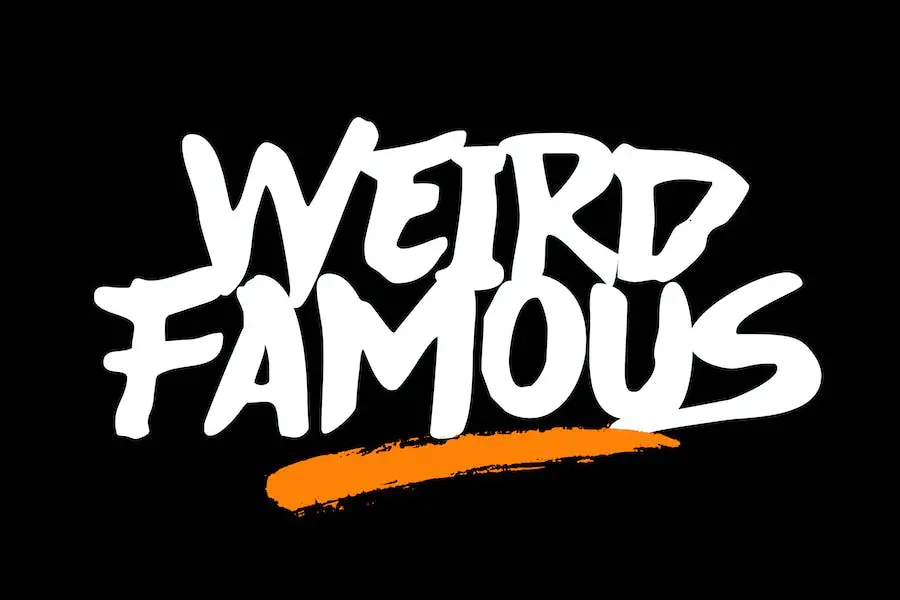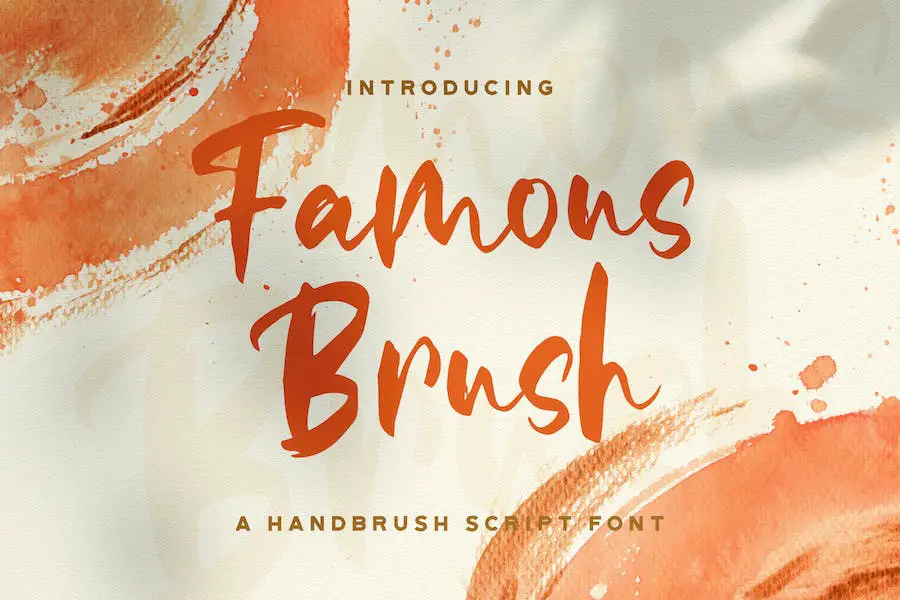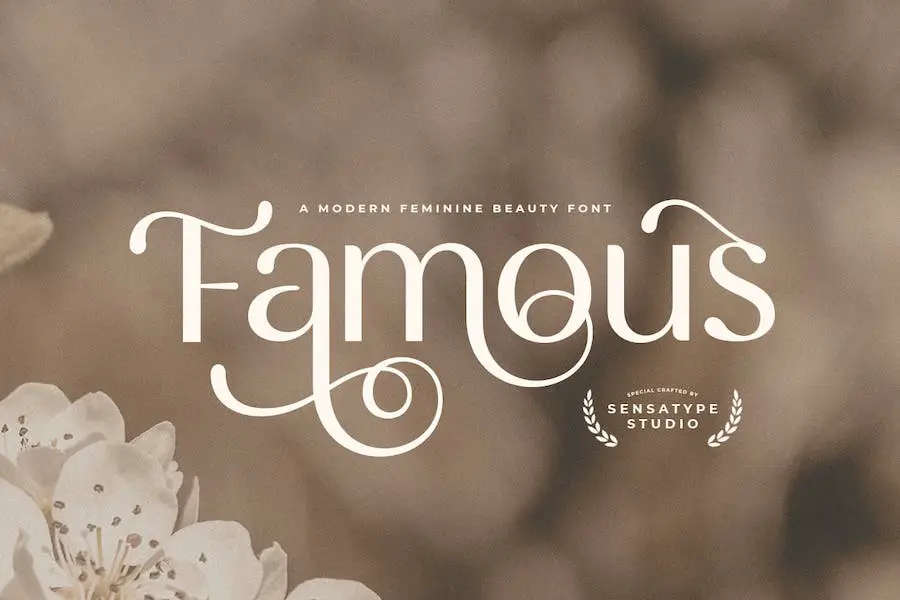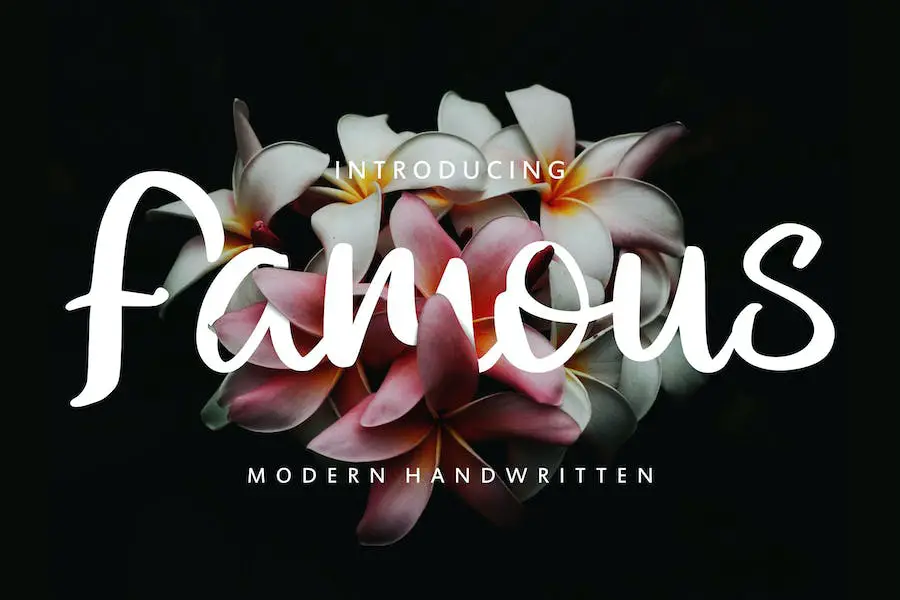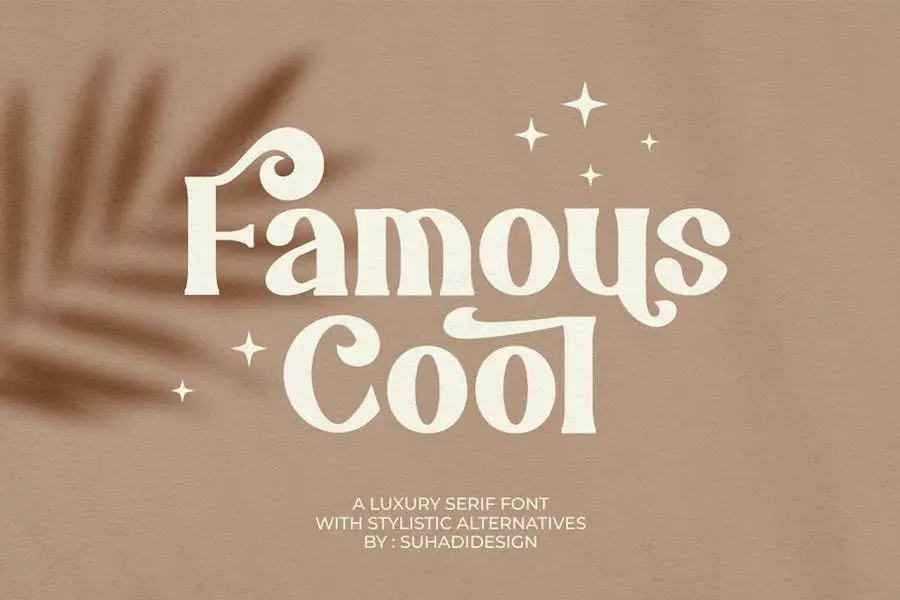
Las 26 fuentes más famosas de 2023 (gratis y premium)
Publicado: 2023-09-22¿Eres un diseñador gráfico en busca de la fuente perfecta para realzar tus proyectos? ¡No busque más! En esta publicación de blog, exploraremos las fuentes más famosas que seguramente mejorarán su trabajo de diseño.
Quizás se pregunte: "¿Qué hace que una fuente sea famosa?" o "¿Cómo pueden estas fuentes mejorar el diseño de mi proyecto?" Bueno, quédate porque tenemos todas las respuestas para ti.
En este artículo, nos sumergiremos en el mundo de la tipografía y mostraremos algunas de las fuentes más icónicas y conocidas que han tenido un impacto significativo en la industria del diseño.
Desde fuentes serif clásicas hasta fuentes de visualización modernas y extravagantes, cubriremos una amplia gama de estilos y su uso. Así que prepárate para inspirarte y descubrir nuevas fuentes que llevarán tus proyectos de diseño al siguiente nivel.
Comencemos nuestro viaje de exploración de fuentes examinando las características de estas fuentes famosas y comprendiendo su popularidad entre los diseñadores. Discutiremos el significado histórico, las asociaciones culturales y el impacto que estas fuentes han tenido en las tendencias de diseño populares.
Con cada fuente, le proporcionaremos datos y estadísticas interesantes, lo que le brindará una comprensión más profunda de su uso y popularidad.
Entonces, ya sea que esté diseñando un logotipo, creando un póster o simplemente necesite una fuente nueva para mejorar su contenido digital, este artículo es su guía para las fuentes más famosas disponibles.
Las mejores fuentes famosas premium
¿Buscas mejorar tus proyectos de diseño? No busques más que nuestra colección seleccionada de las mejores fuentes famosas premium. Estas fuentes seguramente agregarán un toque de sofisticación y creatividad a tu trabajo. ¡Echa un vistazo a los siguientes productos y prepárate para inspirarte!
Famoso
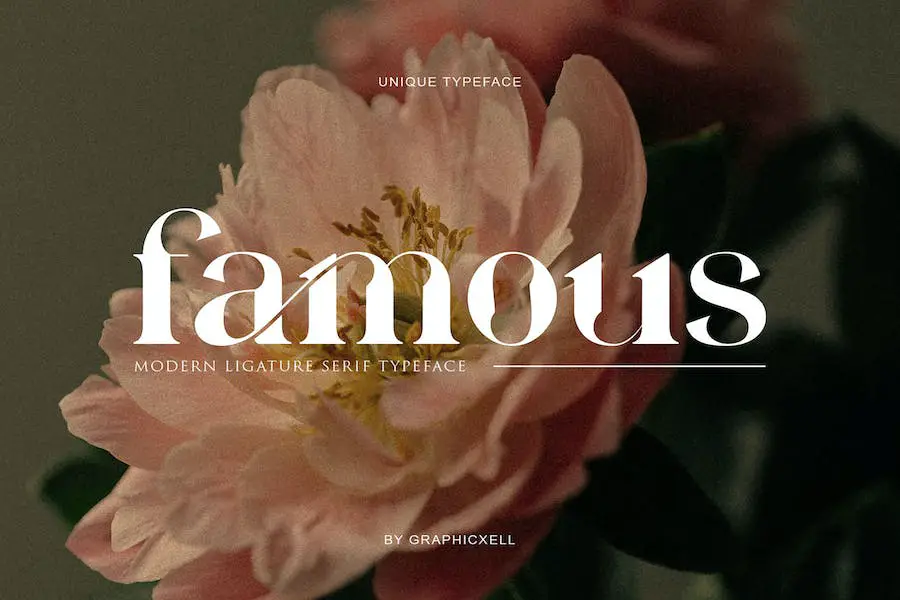
Famous es una fuente Serif que se inspira en famosos logotipos minimalistas. Esta fuente es ideal para diseñadores gráficos que buscan mejorar el diseño de sus proyectos, ya sea creando plantillas, folletos, videos o marcas para publicidad.
Con su estilo elegante y minimalista, Famous añade un toque de profesionalismo y sofisticación a cualquier diseño. Sus líneas limpias y curvas elegantes lo hacen adecuado para una amplia gama de aplicaciones y dan a sus proyectos un aspecto pulido y profesional.
Diseñado específicamente pensando en los diseñadores gráficos, Famous ofrece una gama versátil de opciones. Ya sea que esté trabajando en materiales impresos como folletos y plantillas o creando videos atractivos con fines de marketing, esta fuente realzará sus diseños y los hará destacar.
El famoso diseño minimalista inspirado en el logotipo de esta fuente la convierte en una excelente opción para proyectos de marca. Puede ayudarle a crear una identidad de marca coherente y memorable que deje una impresión duradera en su audiencia.
Llamas famosas
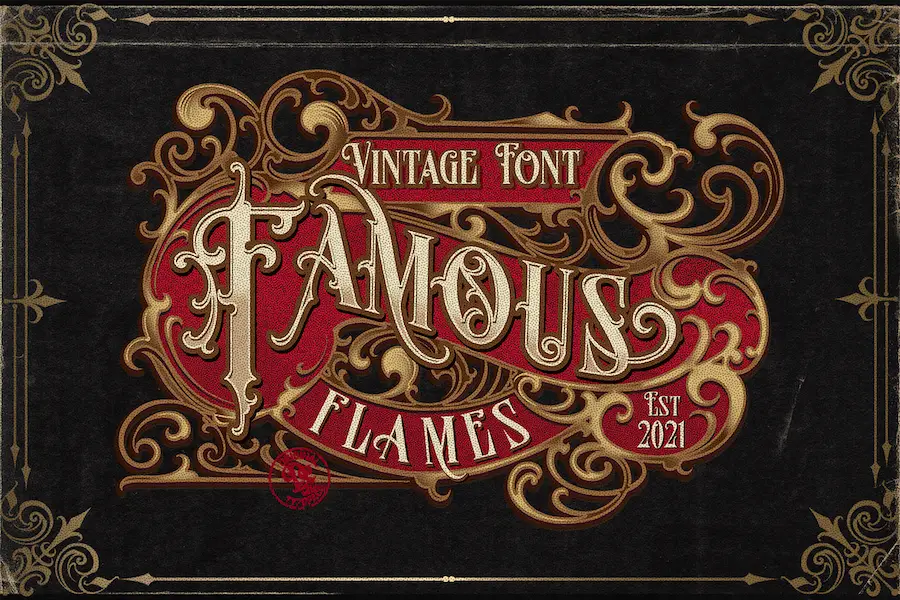
Presentamos Famous Flames, una fuente de letra negra vintage elegante, distinta y muy detallada que es perfecta para agregar un toque de sofisticación a sus proyectos de diseño gráfico.
Esta fuente está diseñada específicamente para mejorar el atractivo visual y el diseño general de los logotipos, lo que la convierte en una opción ideal para los diseñadores gráficos que buscan mejorar su trabajo.
Con Famous Flames, puedes agregar instantáneamente una sensación de encanto y riqueza atemporales a tus diseños. Sus intrincados detalles y su estética vintage crean una apariencia única y cautivadora que seguramente llamará la atención.
Ya sea que estés trabajando en un logotipo para una marca de lujo, un proyecto de inspiración vintage o simplemente quieras agregar un toque de elegancia del viejo mundo, esta fuente lo tiene cubierto.
La belleza de Famous Flames radica en su versatilidad. Puede combinarse perfectamente con una amplia gama de estilos y temas de diseño, permitiéndole explorar diversas posibilidades creativas.
Desde lo clásico y tradicional hasta lo vanguardista y moderno, esta fuente se adapta sin esfuerzo a diferentes contextos de diseño, lo que la convierte en una valiosa adición a su conjunto de herramientas tipográficas.
Morgan famoso
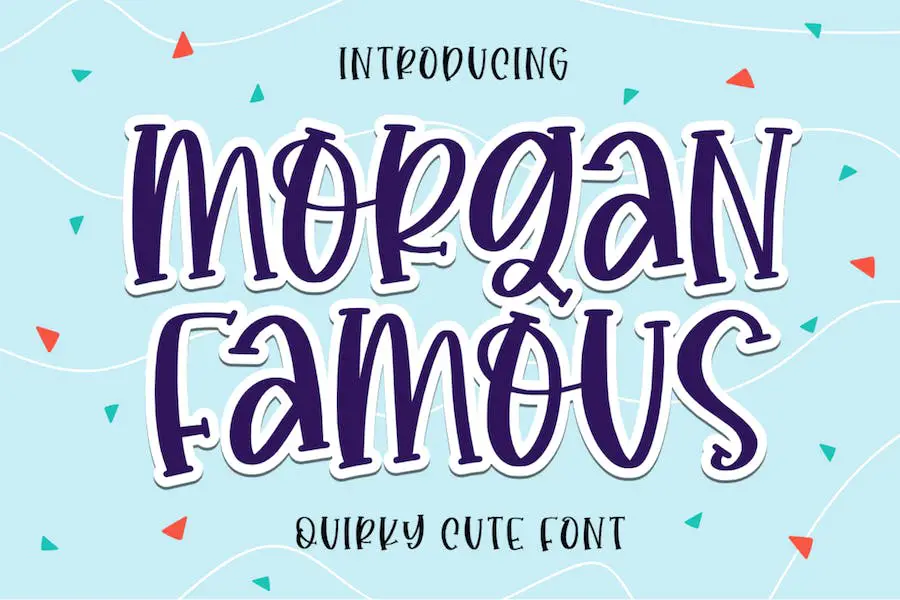
Morgan Famous es una fuente manuscrita linda e informal que irradia una sensación increíblemente amigable. Si eres un diseñador gráfico que busca mejorar el diseño de tu proyecto, esta fuente es definitivamente una que debes considerar. Su ambiente relajado y accesible lo hace perfecto para una amplia gama de proyectos.
Con Morgan Famous, puedes agregar un toque personal a tus diseños. El estilo escrito a mano añade un elemento humano, haciendo que tus creaciones se sientan cálidas y auténticas.
Ya sea que estés diseñando un logotipo, creando gráficos para redes sociales o diseñando invitaciones, esta fuente aportará un toque único y personalizado a tu trabajo.